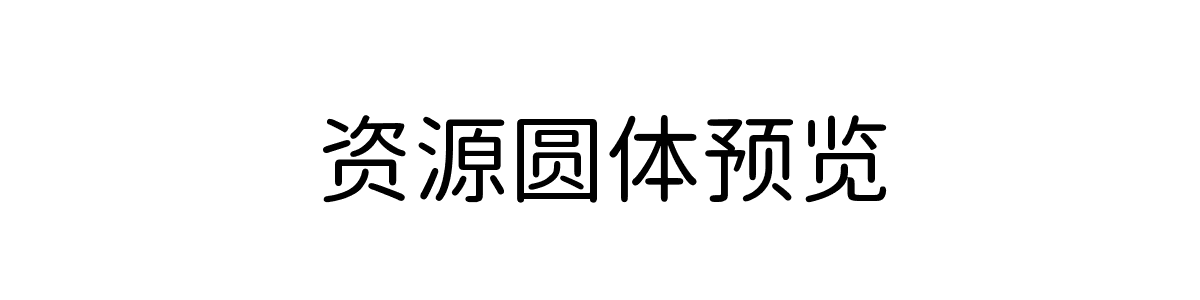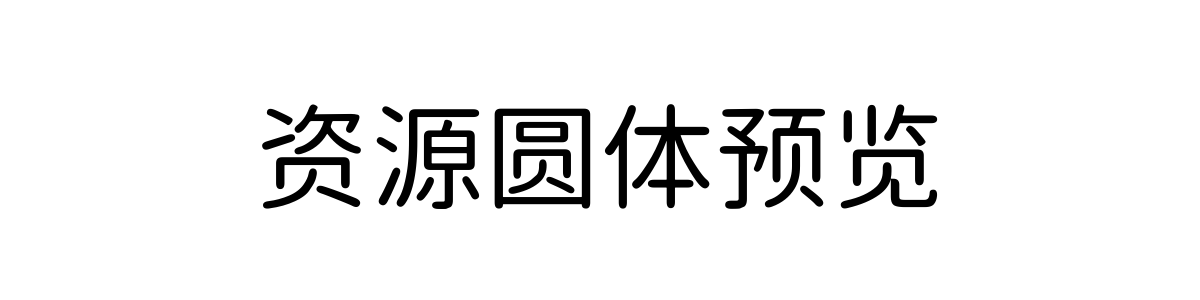
资源圆体
资源圆体(Source Han Rounded)是在思源黑体(Source Han Sans)基础上改造而成的开源圆体字库,它完整保留了原版优秀的字形结构和超大字库容量,只在细节上做了柔和化处理,把笔画末端和转角都改成顺滑的圆角,整体风格更温润,也更具现代感。
字体一共提供七种字重,对简体中文支持十分完善,日常使用几乎不会出现缺字问题。
字体风格
资源圆体的核心气质就是圆润柔和,原本硬朗的直角被统一处理成圆角,去掉了尖锐感,看上去亲切又友好。温和耐看的同时也不失时尚感,圆角设计能有效缓解长时间阅读的视觉疲劳,用在界面、排版里会显得轻盈活泼,适配各种轻松现代的设计场景。